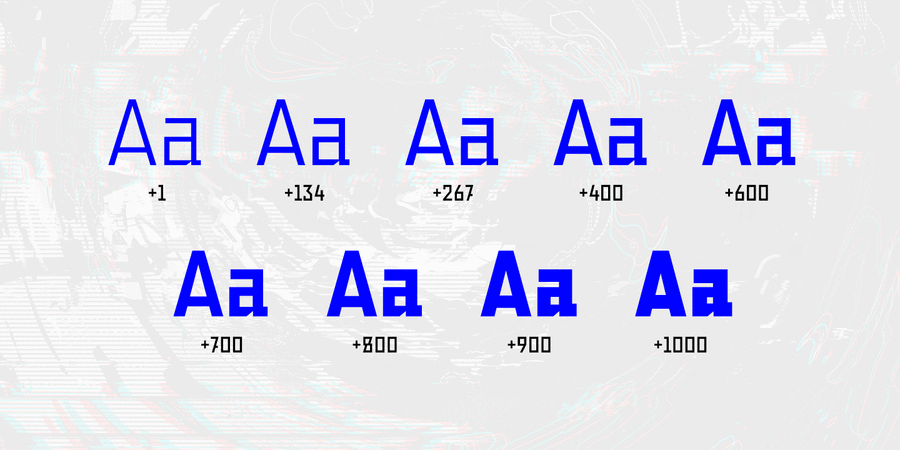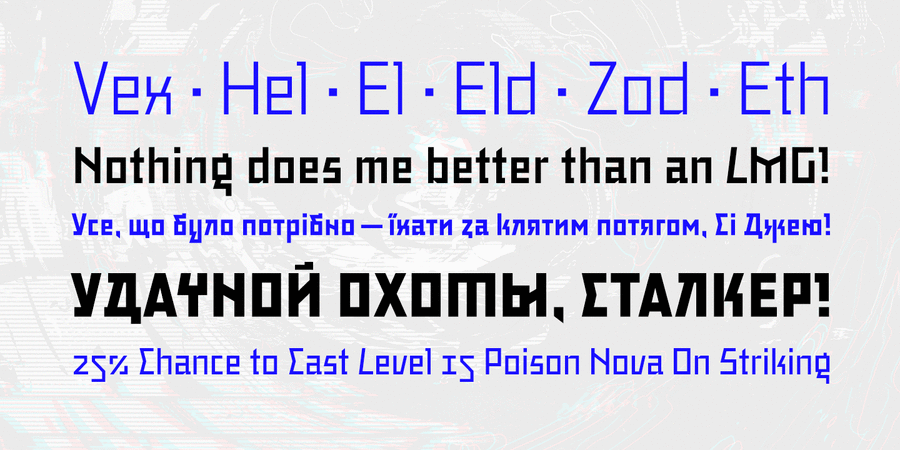
Варіативний шрифт Легасов призначений для логотипів, заголовків, обкладинок книг та фірмового стилю. Ви можете використовувати його також для невеличких текстових фрагментів. Це сучасний паличний геометричний гротеск, натхненний українським модернізмом 20-го століття. Він має динамічну форму знаків та авангардний характер. Шрифт розробили Сергій Макаренко та Кирило Ткачов у 2022 році.
Асоціації з сімейством шрифтів Legasov Variable FontОсобистість і характер гарнітури:
серйозний, переконливий, твердий, залізний, надійний, мужній, впевнений, сталевий, ностальгічний, тоталітарний, стабільний, гучний, рівний, сильний, кондовий, стійкий, політичний, комуністичний, революційний, сміливий, пролетарський, точний, прямокутний, індустріальний, техногенний, військовий, армійський, солдатський, урбаністичний, грубий, робочий, мотивуючий, залізничний, амбітний, міський, незграбний, гострий, жорсткий, ламаний, рубаний, елементарний, різкий, чіткий, брутальний, ігровий, міцний
війна, армія, зброя, машинобудування, прапор, мітинг, політика, шахта, завод, металургія, верстат, інструмент, будівництво, будматеріали, тара, склад, порт, ящик, патрони, архітектура, конструктор, креслення, техніка, промисловість, електростанція, енергетика, ремонт, урбаністика, депо, шахтар, шолом, уніформа, вагон, авіація, літак, страйкбол, взуття, коворкінг, залізниця, Місто, робочий, страйк, Протест, кубики, лего Гарнітура має ознаки стилів: